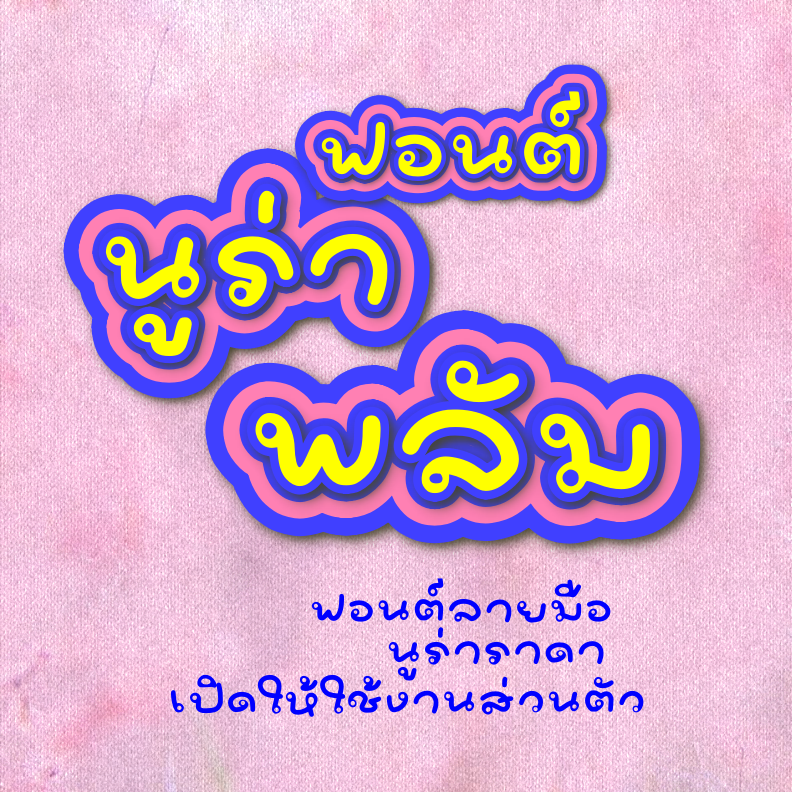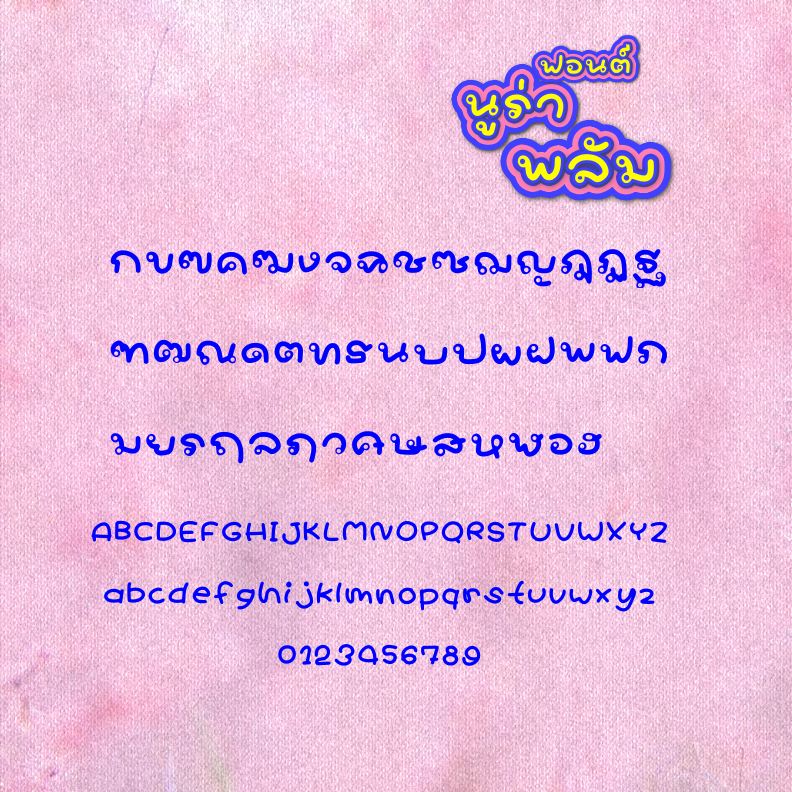
นูร่าพลัม (Nura plum)
ฟอนต์ลายมือน่ารัก ฟอนต์ตัวอวบ  มีความโยเย สนุกสนาน เหมาะทำหัวข้อ หรือข้อความสำหรับโฆษณา  มีด้วยกัน  3 น้ำหนัก  คือ บาง ปกติ หนา